Ketika membicarakan desain bertema musim panas atau summer biasanya akan memiliki elemen yang merepresentasikan musim panas. Desain bertema musim panas memiliki tampilan yang segar, cerah dan menyenangkan, maka dari itu elemen yang digunakan seringkali memiliki warna cerah dan tipografi yang ramah. Untuk font yang bisa merepresentasikan desain musim panas seringkali memiliki dekorasi berupa elemen musim panas.
Ketika memikirkan musim panas sebagian orang akan teringat dengan pantai, pohon palem, ombak hingga buah-buahan musim panas. Tidak hanya elemen gambar dan ilustrasi yang bertema musim panas, desain juga perlu memiliki font yang tepat. Ada banyak font unik yang bertema musim panas dan khusus digunakan untuk mencerminkan desain summer yang segar.
DEKORASI ELEMEN MUSIM PANAS
Untuk menciptakan tema musim panas, penting untuk tahu elemen visual yang sering digunakan untuk merepresentasikan musim panas. Elemen ilustrasi bertema musim panas seringkali terkait pantai. Berikut beberapa elemen visual yang sering ditemui dalam desain bertema musim panas, termasuk ditemui sebagai dekorasi font musim panas.
Ice Cream dan Lelehan Ice Cream
Musim panas yang identik dengan cuaca panas selalu berdampingan dengan elemen yang menyegarkan seperti ice cream. Dekorasi ice cream atau berupa lelehan sering menghiasi desain grafis bertema musim panas. Ilustrasi gambar ice cream akan terlihat cocok untuk merepresentasikan musim panas sehingga banyak digunakan untuk desain poster atau desain postingan media sosial.
Pohon Palem
Menciptakan desain bertema summer tanpa menambahkan gambar pohon palem rasanya ada yang kurang. Pohon yang banyak ditemui didaerah pantai dan negara tropis ini sangat cocok untuk merepresentasikan musim panas. Dalam desain bertema summer pohon palem digunakan sebagai dekorasi, terkadang hanya berupa daunnya saja.
Seringkali pohon palem digunakan dalam bentuk siluet untuk menciptakan visual menarik. Dekorasi pohon palem juga bisa digunakan untuk dekorasi atau tekstur pada latar belakang dan font summer.
Ilustrasi atau Siluet Pantai
Desain musim panas juga umum memiliki ilustrasi atau gambar pantai untuk menunjukkan summer yang menyegarkan. Gambar pantai dalam poster biasanya untuk mempromosikan pariwisata atau event di dekat pantai. Sementara ilustrasi atau siluet pantai digunakan untuk merepresentasikan summer dalam bentuk ilustrasi sederhana.
Gambar pantai, ombak, palem dan sunset menjadi ciri khas musim panas bertema pantai negara tropis. Terkadang ada gaya font yang terinspirasi dari tema musim panas dengan hurufnya memiliki dekorasi seperti ombak dan pohon palem. Siluet pantai sering juga digunakan untuk desain logo, poster summer festival, hingga kemasan produk summer.
Buah-buahan Tropis
Musim panas identik dengan berbagai hal di daerah tropis termasuk buah-buahan. Dalam desain grafis bertema summer juga banyak menggunakan elemen gambar buah-buahan segar tropis. Gambar buah-buahan dapat digunakan sebagai pola, dekorasi dan menciptakan kesan segar. Ilustrasi buah sederhana yang identik dengan summer adalah buah semangka, nanas, dan jeruk.
Bunga-bunga
Tidak hanya buah-buahan elemen gambar yang merepresentasikan musim panas dapat memiliki gambar bunga-bunga. Gambar atau ilustrasi bunga tidak hanya digunakan dalam desain musim semi tetapi juga musim panas. Biasanya dia bunga-bunga yang ditemui di negara tropis yang akan digunakan untuk merepresentasikan musim panas.
7 FONT UNTUK DESAIN MUSIM PANAS YANG UNIK
Untuk menciptakan tampilan desain musim panas yang merepresentasikan kesegaran summer, pilih kombinasi elemen summer yang relevan. Desain grafis bertema summer harus memiliki gaya font yang sesuai dengan temanya. Berikut beberapa rekomendasi font unik untuk menciptakan nuansa musim panas1:
Hawaiian Dreams
Jika membicarakan desain summer biasanya juga mengingatkan dengan hawai, tema desain hawai seringkali menjadi khas musim panas. Font summer dengan tema musim panas hawai ini memiliki huruf tebal, lebar dan memiliki dekorasi ala hawai. Huruf dalam jenis font ini memiliki dekorasi berupa bunga dan daun khas hawaii.
Bentuk font tebal dengan dekorasi bunga ini memiliki pinggiran huruf yang bergelombang dan menciptakan tampilan ramah. Pola dalam font ini menciptakan tampilan segar ala musim panas di hawaii. Gunakan font ini untuk poster bertema musim panas yang segar dan unik.
Font Palmspring
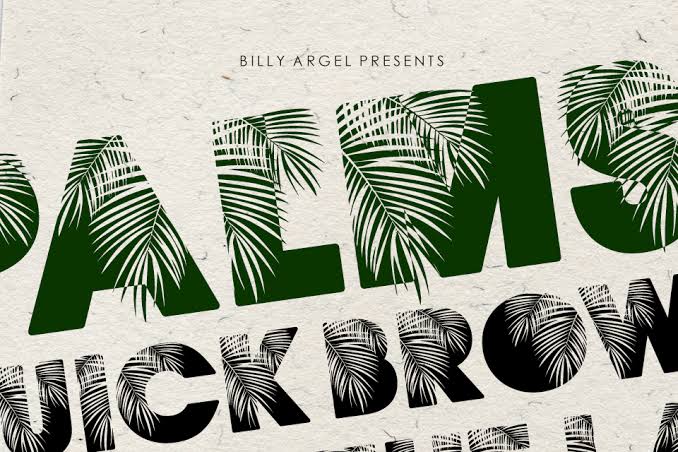
Jenis font ini memiliki huruf tebal dengan dekorasi pohon palem sebagai tekstur dan hiasan. Font ini cocok untuk menggambarkan kesegaran musim panas dan efektif untuk digunakan untuk mencerminkan musim panas. Penggunaan font bersih dengan dekorasi pohon palem ini terlihat unik, tetapi masih memiliki keterbacaan yang baik.
Font dengan tampilan yang unik ini akan cocok jika digunakan untuk desain poster, desain kaos musim panas, dan desain logo bisnis di dekat pantai. Setiap huruf dalam font ini memiliki dekorasi pohon palem yang dibuat dalam bentuk whitespace. Tekstur daun palem tidak lantas membuat teks menjadi sulit dibaca.
Baca juga: Kombinasi Font dalam Desain Grafis sebagai Strategi Branding
Beach Crush
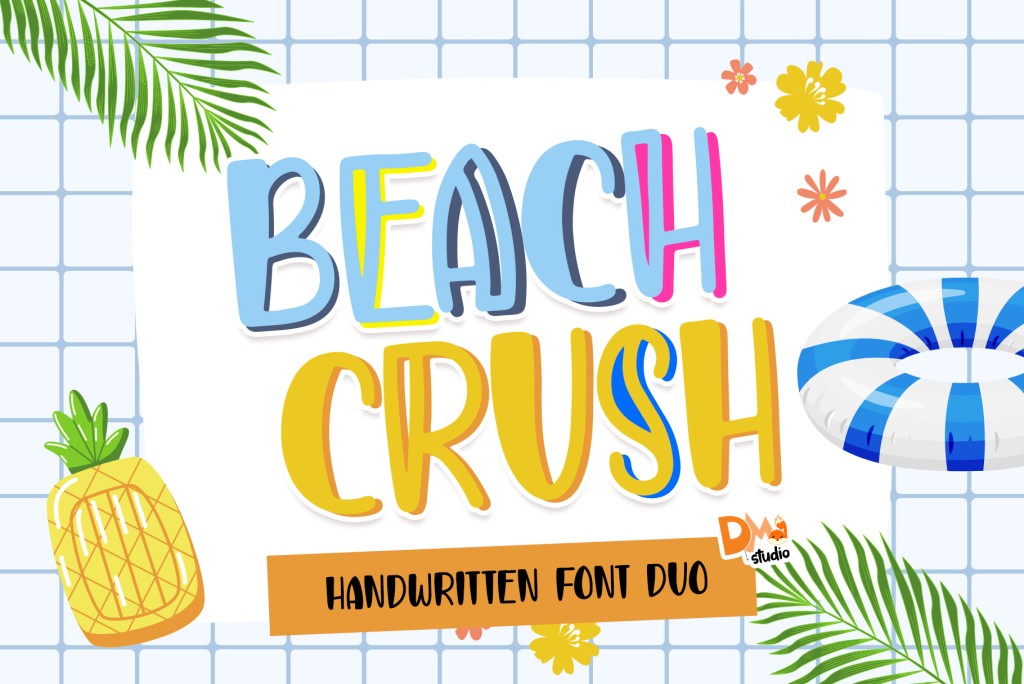
Tampilan font yang ramah dan berkesan alami seperti jenis font handwritten ini juga cocok untuk menciptakan tema summer. Font handwritten satu ini tidak memiliki gaya huruf bersambung tetapi font terlihat dibuat mengikuti arah tulisan tangan. Gaya hurufnya yang tebal, dengan ujung ramah cocok untuk tema musim panas.
Dalam penggunaan font dengan gaya tulisan tangan ini bisa digunakan dengan warna cerah agar menarik perhatian. Tampilan font ini mudah dibaca sehingga bisa digunakan untuk desain logo, poster maupun kemasan.
Summer Festival
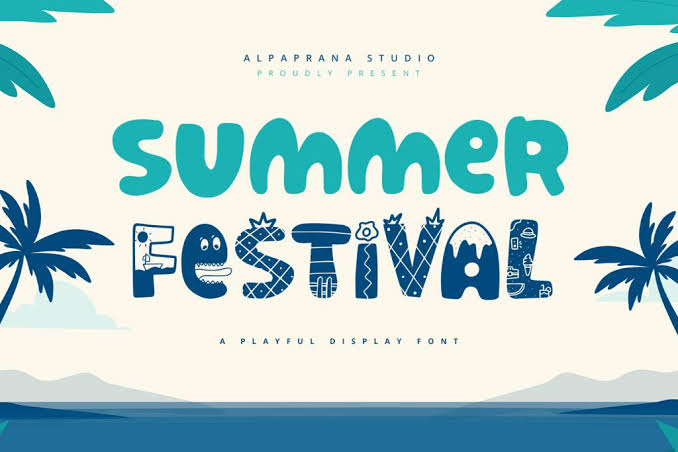
Tipografi yang digunakan dalam desain bertema summer seringkali memiliki tampilan ramah, font bulat, font wavy hinga font dengan dekorasi elemen musim panas. Beberapa huruf dalam jenis font summer festival ini memiliki dekorasi yang unik. Elemen musim panas yang digunakan dalam beberapa hurufnya merepresentasikan summer dengan baik.
Beberapa font memiliki dekorasi seperti tekstur buah nanas, es krim, gambar laut dan elemen musim panas lainnya. Bentuk huruf yang bulat dan tebal membuatnya terlihat ramah dan semakin cocok untuk menciptakan tema summer yang segar. Font bulat yang ramah akan menciptakan tampilan harmonis dengan elemen musim panas lainnya.
Sand Beach Font
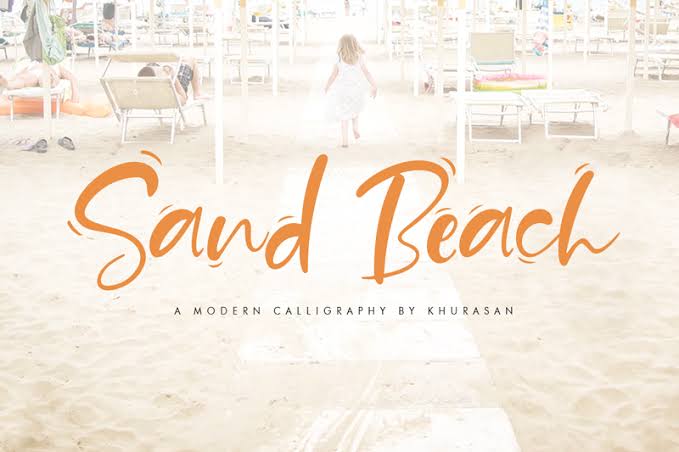
Gaya font script yang ramah dengan ujung huruf dan sudut melengkung menciptakan tampilan ramah. Handwritten style ini terlihat ramah dan cocok untuk digunakan dalam desain bertema musim panas. Font ini memiliki dekorasi berupa garis-garis tipis yang membuat huruf terlihat lebih menarik.
Penggunaan font ini akan cocok untuk bisnis yang bertema musim panas, tampilan font ramah ini memiliki tampilan seperti pasir pantai yang halus. Jenis font flowing ini terlihat mengalir dengan halus seperti pasir pantai dan cocok untuk digunakan pada poster atau headline summer.
Baca juga: Rekomendasi Font untuk Desain Grafis Bertema Sport
Sunset Club Font
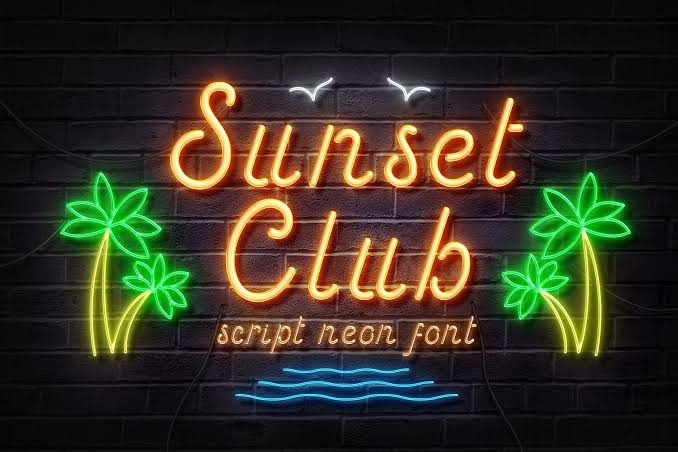
Font yang digunakan untuk musim panas terkadang juga mengambil inspirasi dari budaya yang identik dengan musim panas. Musim panas biasanya identik juga dengan sunset pantai yang indah dan klub-klub musim panas. Gaya font yang memiliki tampilan unik ini cocok untuk digunakan sebagai logo bisnis di dekat pantai.
Font sunset club yang memiliki gaya huruf mengikuti tulisan tangan ini memiliki tampilan alami, natural, dan sederhana. Huruf mudah dibaca dan bisa digunakan untuk merepresentasikan tema summer yang ramah. Font dengan ujung yang melengkung dan tidak gandeng ini mudah untuk dibaca.
Tropic Fresh
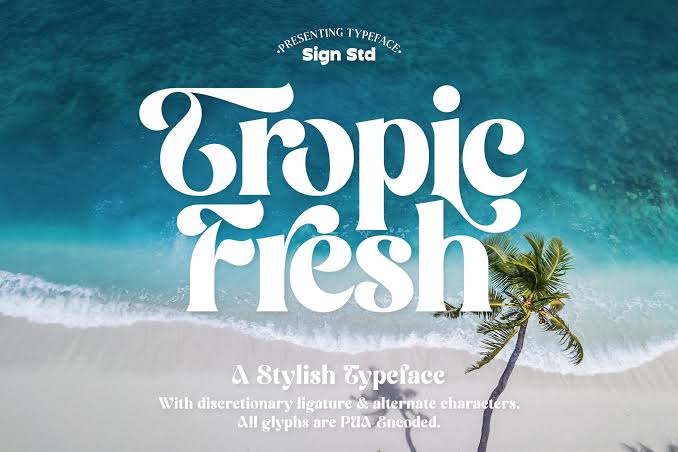
Desain grafis bertema summer juga bisa memiliki gaya font yang unik dengan ujung melengkung. Bentuk huruf dalam font ini terlihat stylish, hurufnya bergaya melengkung dengan ujung lancip. Penggunaan terlihat cocok untuk menciptakan kesan fresh untuk desain summer.
Font tropic fresh ini akan cocok untuk dijadikan judul headline summer, tipografi desain minuman summer hingga poster untuk festival summer. Huruf yang tebal akan memudahkan jenis font ini menarik perhatian dan mudah untuk dibaca.
Ketika ingin menciptakan desain grafis bertema summer atau musim panas, pilih elemen-elemen visual yang mencerminkan musim panas. Desain bertema summer seringkali memiliki warna cerah dan segar, ilustrasi pantai dan pohon pelem, selain itu juga memiliki gaya huruf tebal, amah dan bulat. Beberapa rekomendasi jenis font unik dan menyegarkan tersebut cocok untuk desain bertema musim panas.